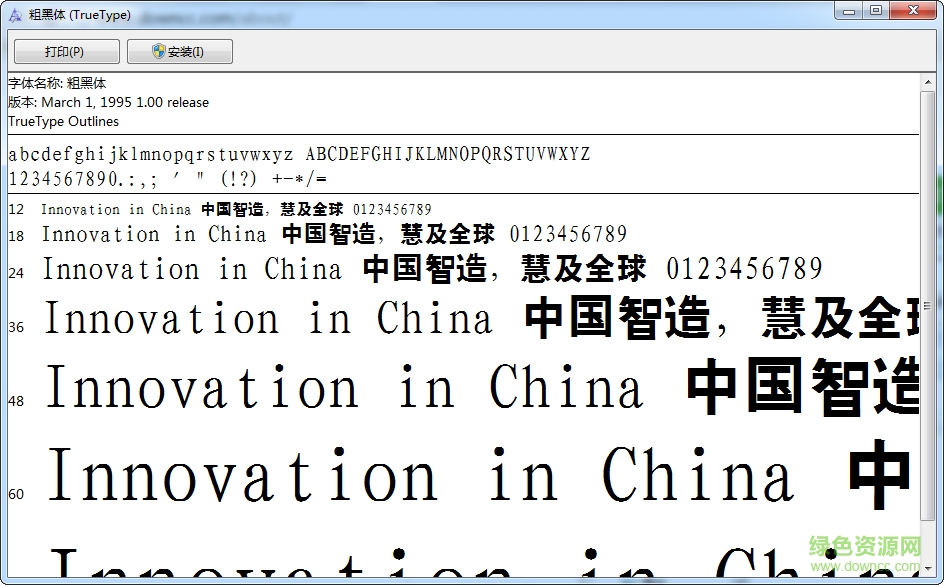
rs_cuhei字体
rscuhei字体是一款四通利方粗黑字体,一笔一画都十分工整,线条弧度稳定,厚实有力,醒目张扬,阅读效果非常清晰,常常用于文本标题、宣传标语等方面,在生活中一般都是比较常见的,也非常的方便使用,有需要者欢迎在绿色资源网下载!
黑体字体介绍
黑体,是中文一类字体的名称,与白体相反,特点是没有衬线装饰,笔划粗壮有力,撇捺等笔画不尖,使人易于阅读,由于其醒目的特点,常用于标题,导语,标志等等。
现代字体风格
字体造型规整,富于力度,给人以简洁爽朗的现代感,有较强的视觉冲击力,这种个性的字体,适合于机械科技等主题。